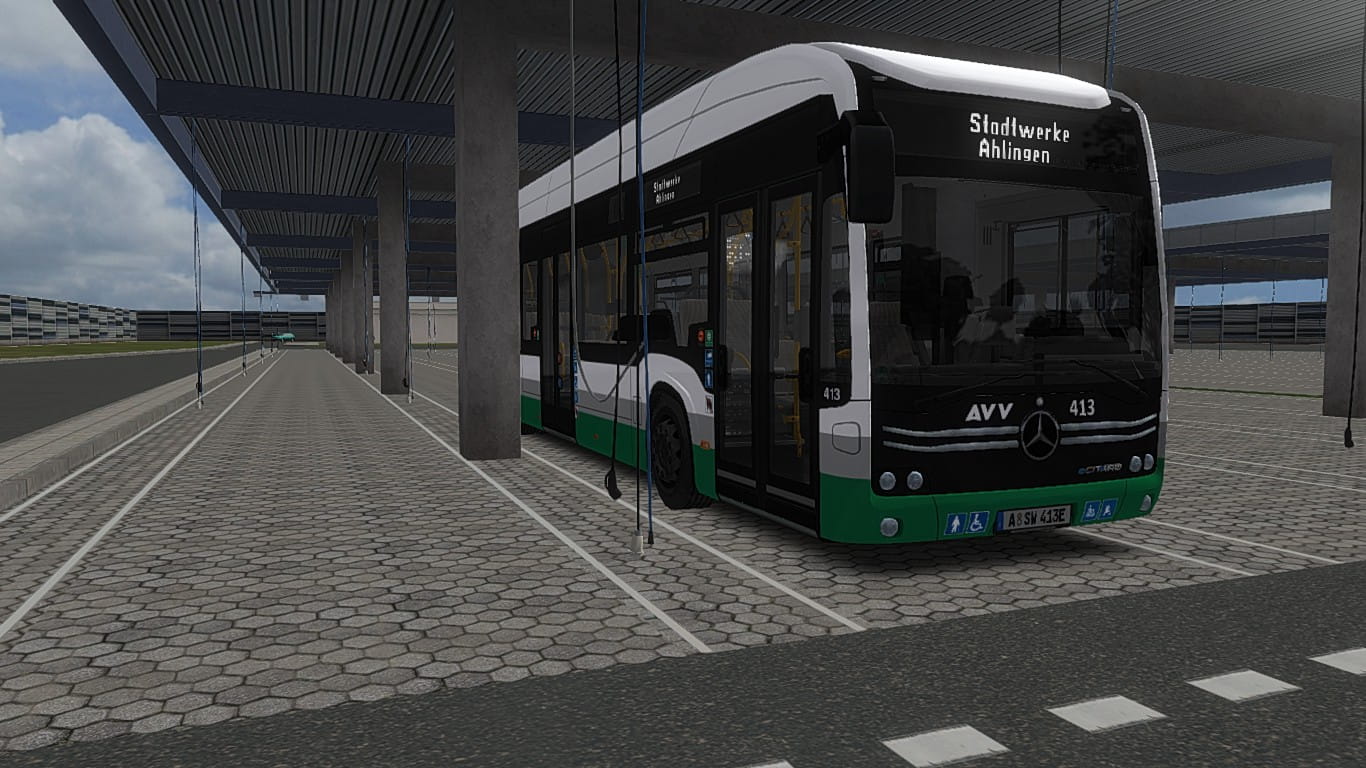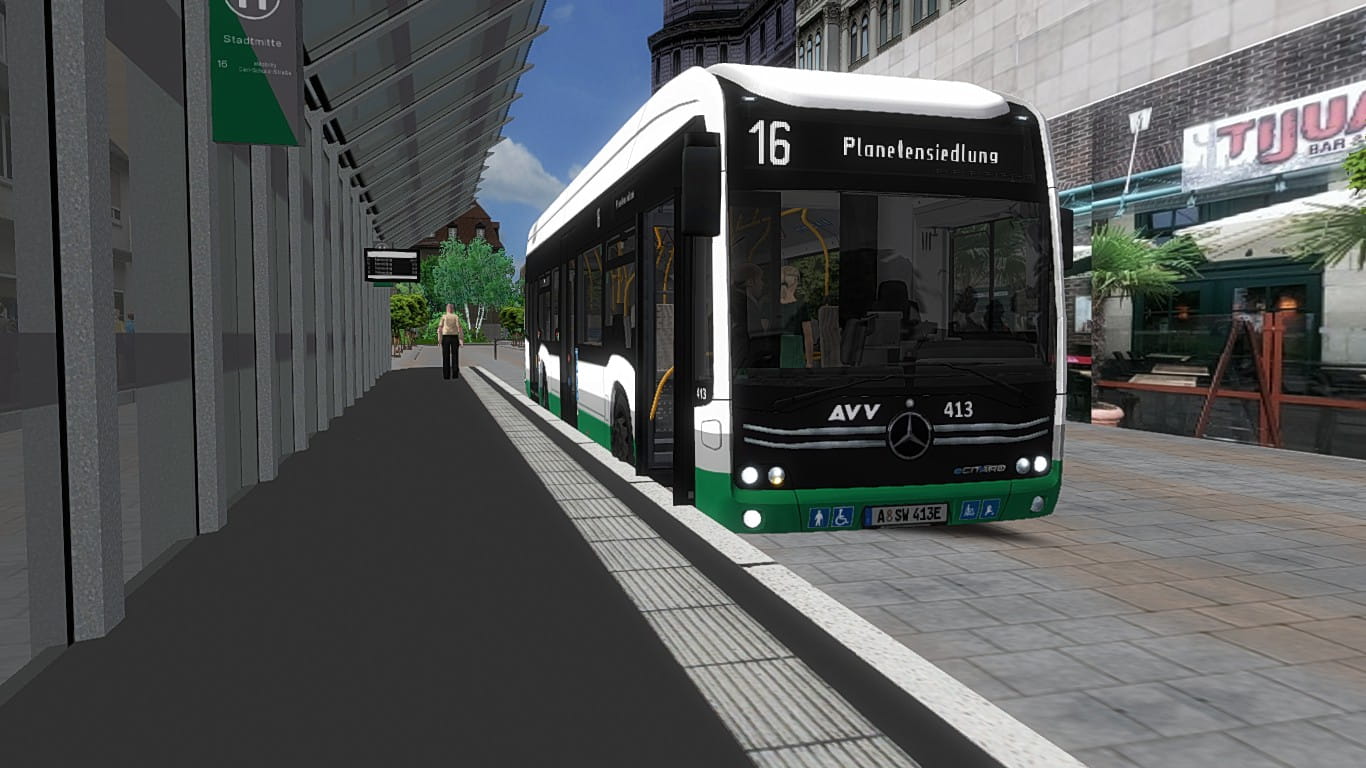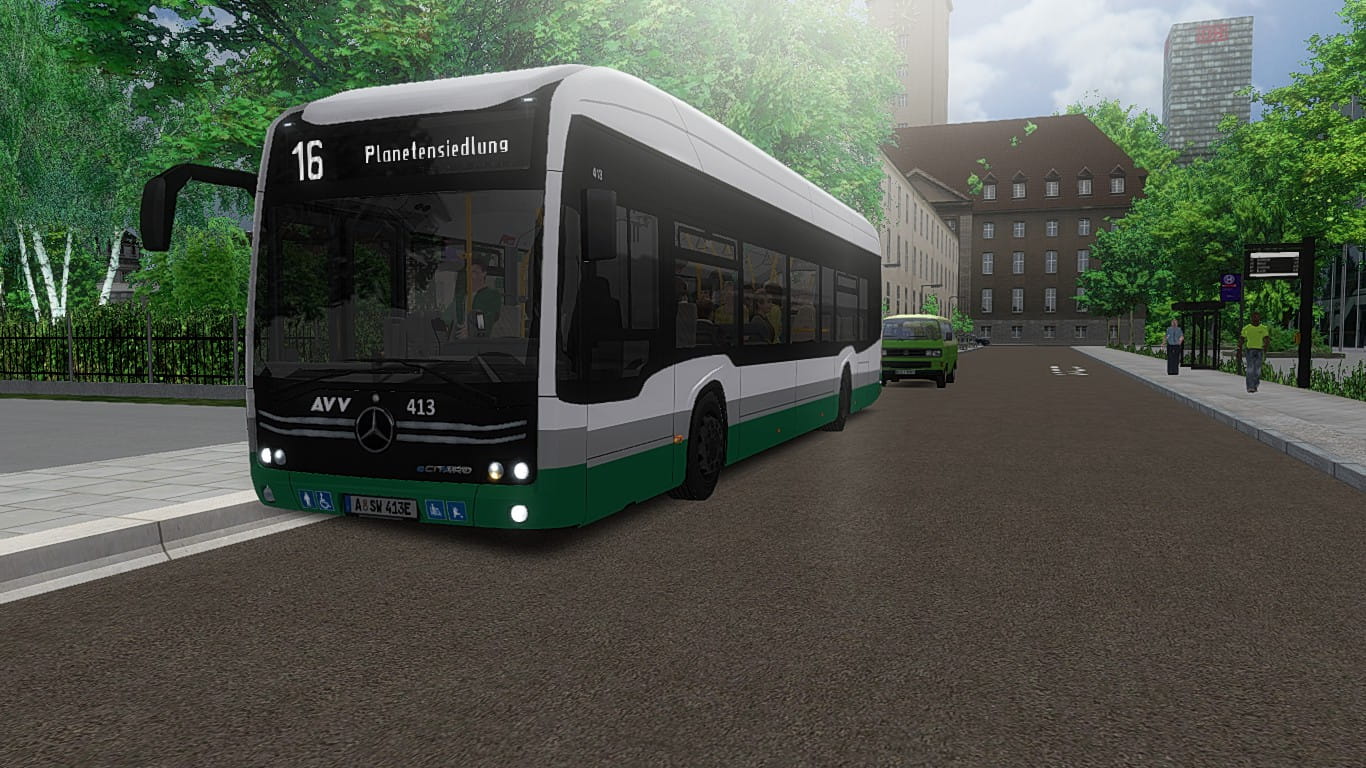
Dickere LAWO-Fonts für den eCitaro 1.0.0
Dickere LAWO-Fonts für den eCitaro
heute habe ich ein paar dickere LAWO-Fonts.
Die Fonts sind von @Oberpfalz3D erstellt worden, und ich habe sie gereuploaded für den eCitaro.
Dazu empfehle ich euch den Mod für die Weiße Matrix für den eCitaro von @Berlin|BVG|Lucas.
Sonst wünsche ich euch noch viel Spaß mit den dickeren Matrixfonts!
Benötigt man die andere "Weisse-Matrix-Mod" oder wird es nur empfohlen?
Wird die orange "Original"-Matrix überschrieben?
ihr dürft es euch aussuchen.
Es ist völlig egal, hier geht es nur drum, die Fonts besser, größer und heller zu erkennen.
• Es wird empfohlen, da wie ich finde es in weiß deutlich besser aussieht.
Wenn ihr den Mod für die weiße Matrix nicht herunterladet, habt ihr die orangene.
Diese wird nicht überschrieben, egal ob weiß, orange, grün oder rot. Hier geht es um die Schriftart. Diese ist dicker wie sonst
Ich find den Mod ganz nett gemacht. Mir gefällt er und ich werde ihn verwenden... die dickere weiße Schriftart sticht meiner Meinung nach besser ins Auge und ist besser zu erkennen wie das Original.